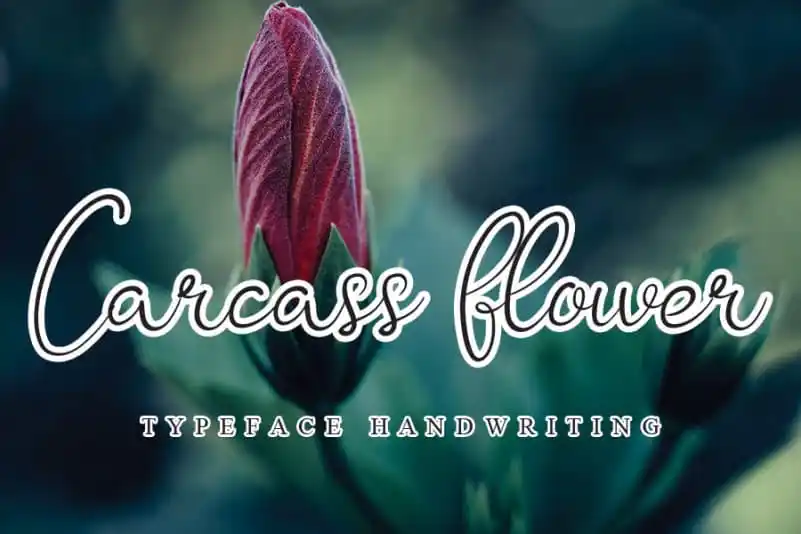
A fonte ‘Carcass Flower Font’ é uma delicada letra escrita à mão que oferece um toque elegante e fino ao seu design. Perfeita para uso em convites, cartas de agradecimento, frases motivacionais ou logomarcas, esta font é ideal para aqueles projetos que precisam de uma sensação autêntica e pessoal. A sua natureza escrita à mão confere um toque único e distintivo aos seus trabalhos, tornando-a perfeita para criar um design sofisticado e agradável ao olho. Ideal tanto para aplicar em títulos quanto em textos descritivos, esta font ‘Carcass Flower Font’ tem certamente o seu espaço na sua biblioteca de recursos gráficos. Além disso, ela é perfeitamente compatível com a categoria Handwritten Fonts, onde desempenha um papel fundamental ao fornecer uma opção única para projetos que valorizam a autenticidade e a personalização.